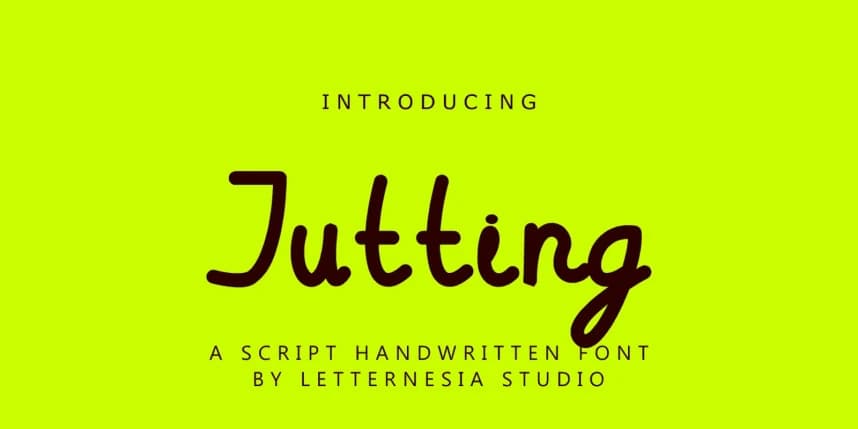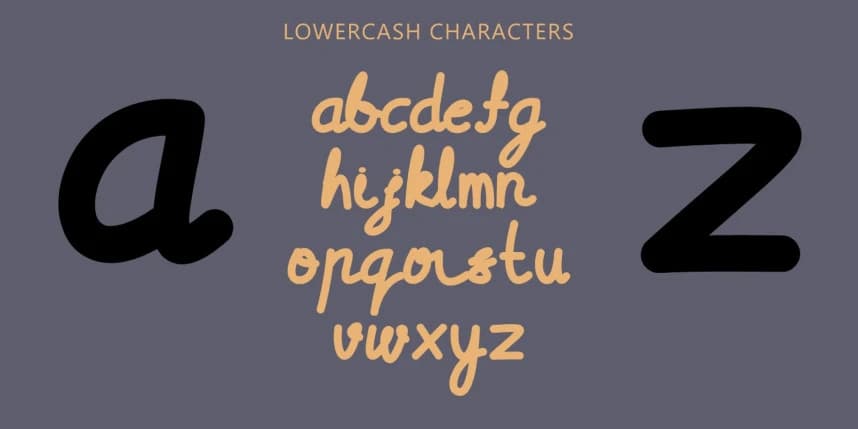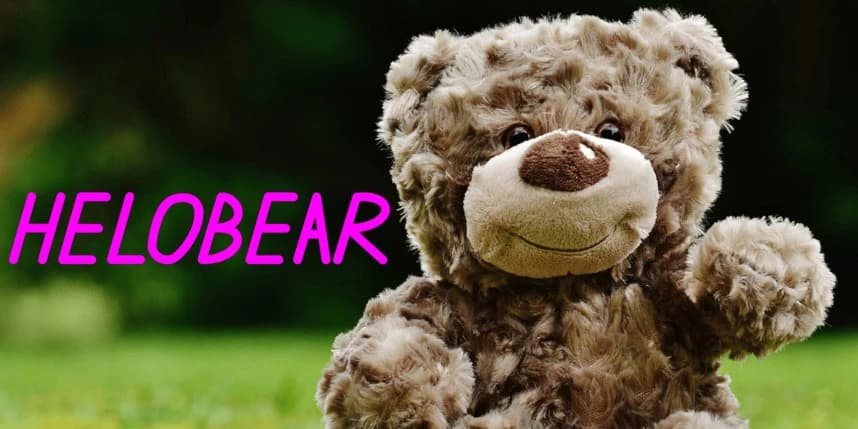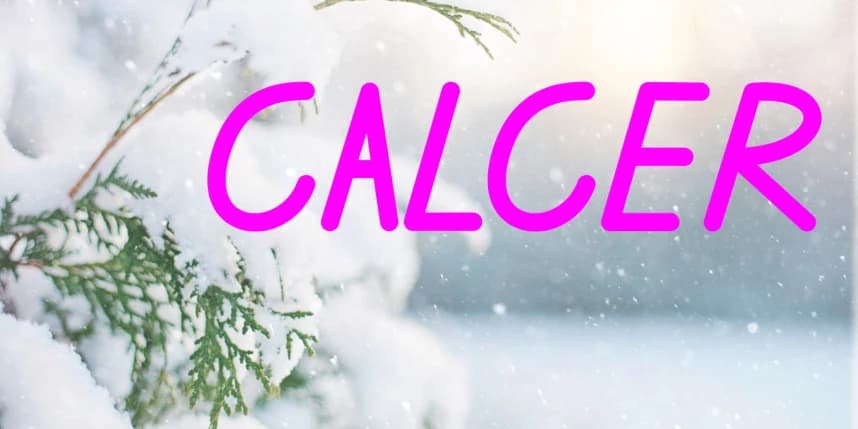
Jutting Script Font
Jutting Script Font, hassasiyeti kişiliğiyle harmanlayan çarpıcı bir görüntü yazı tipidir. Köşeli kesimler, temiz kenarlar ve cesur geometrik bir yapı ile tasarlanan JUTTING, herhangi bir görsel düzenlemede zahmetsizce öne çıkar.
Jutting Script Font, hassasiyeti kişiliğiyle harmanlayan çarpıcı bir görüntü yazı tipidir. Köşeli kesimler, temiz kenarlar ve cesur geometrik bir yapı ile tasarlanan JUTTING, herhangi bir görsel kompozisyonda zahmetsizce öne çıkar.